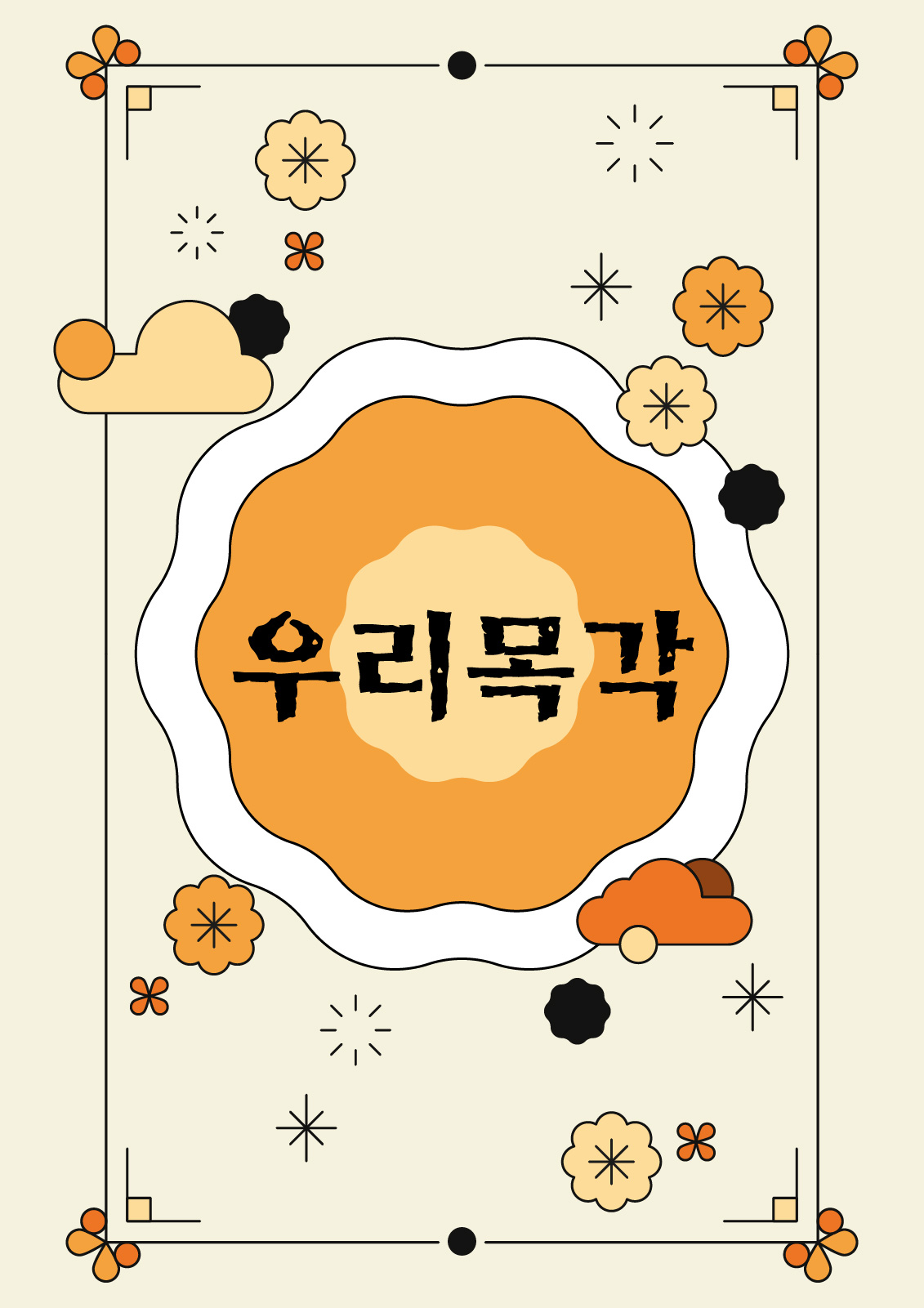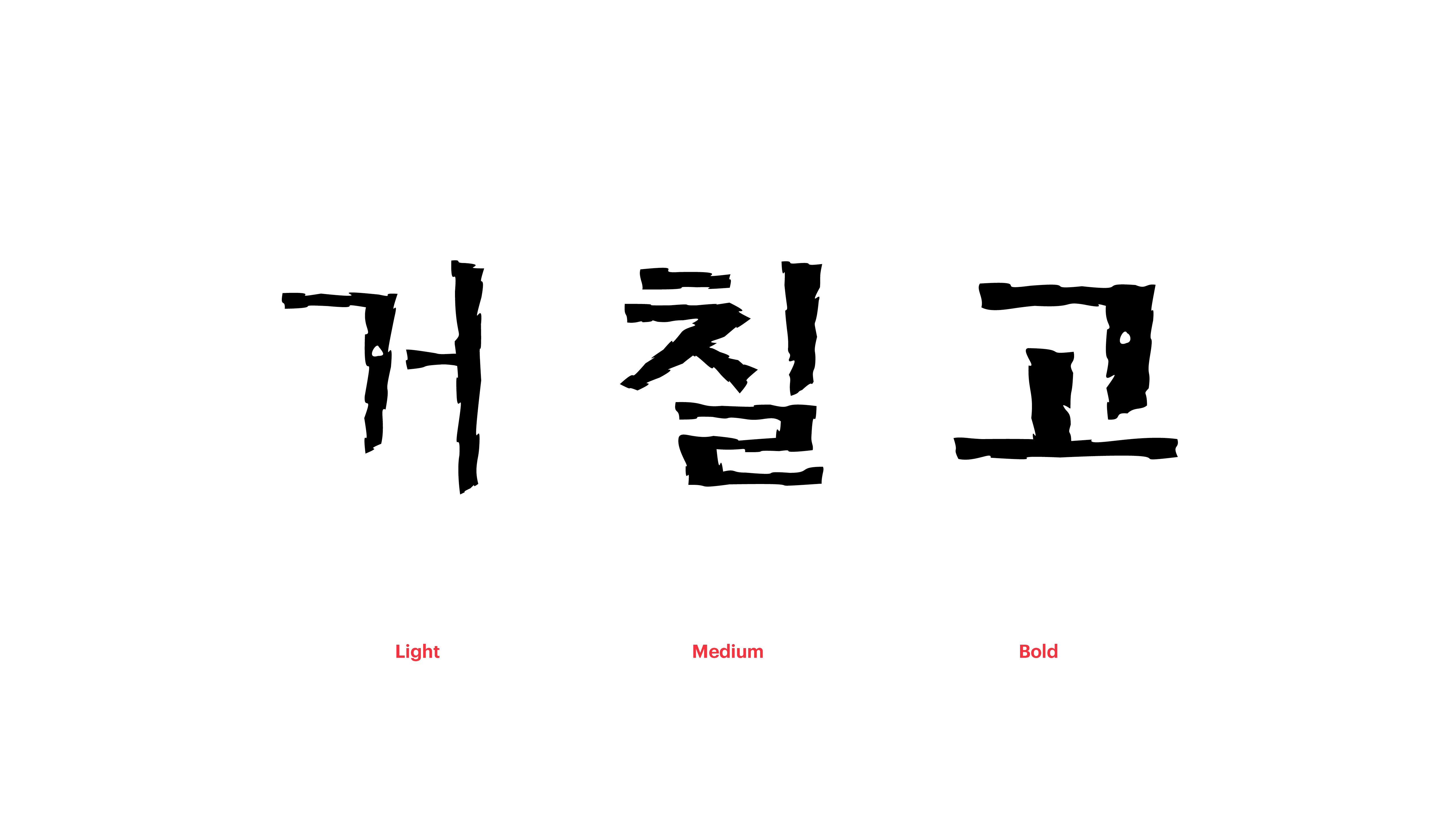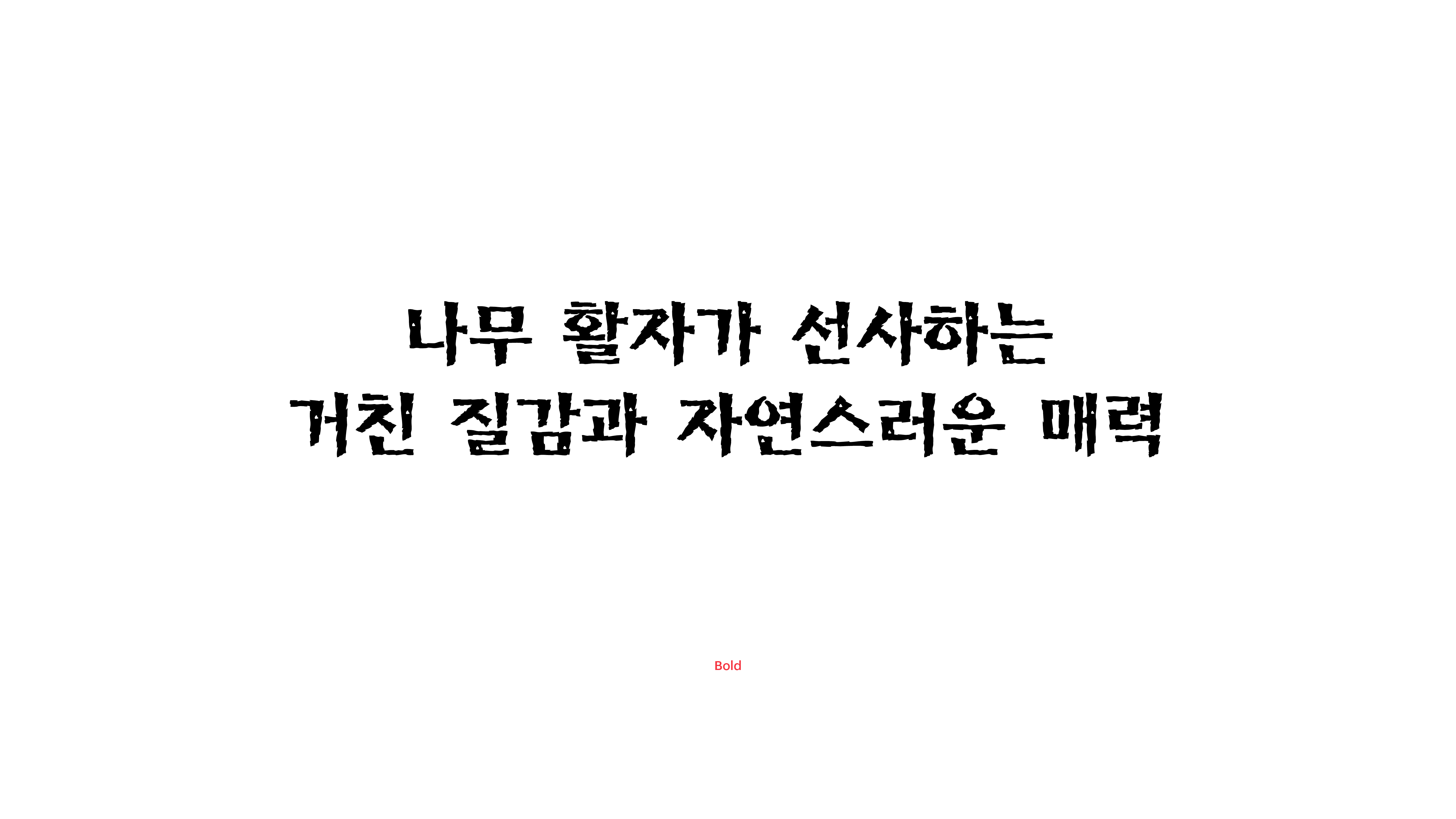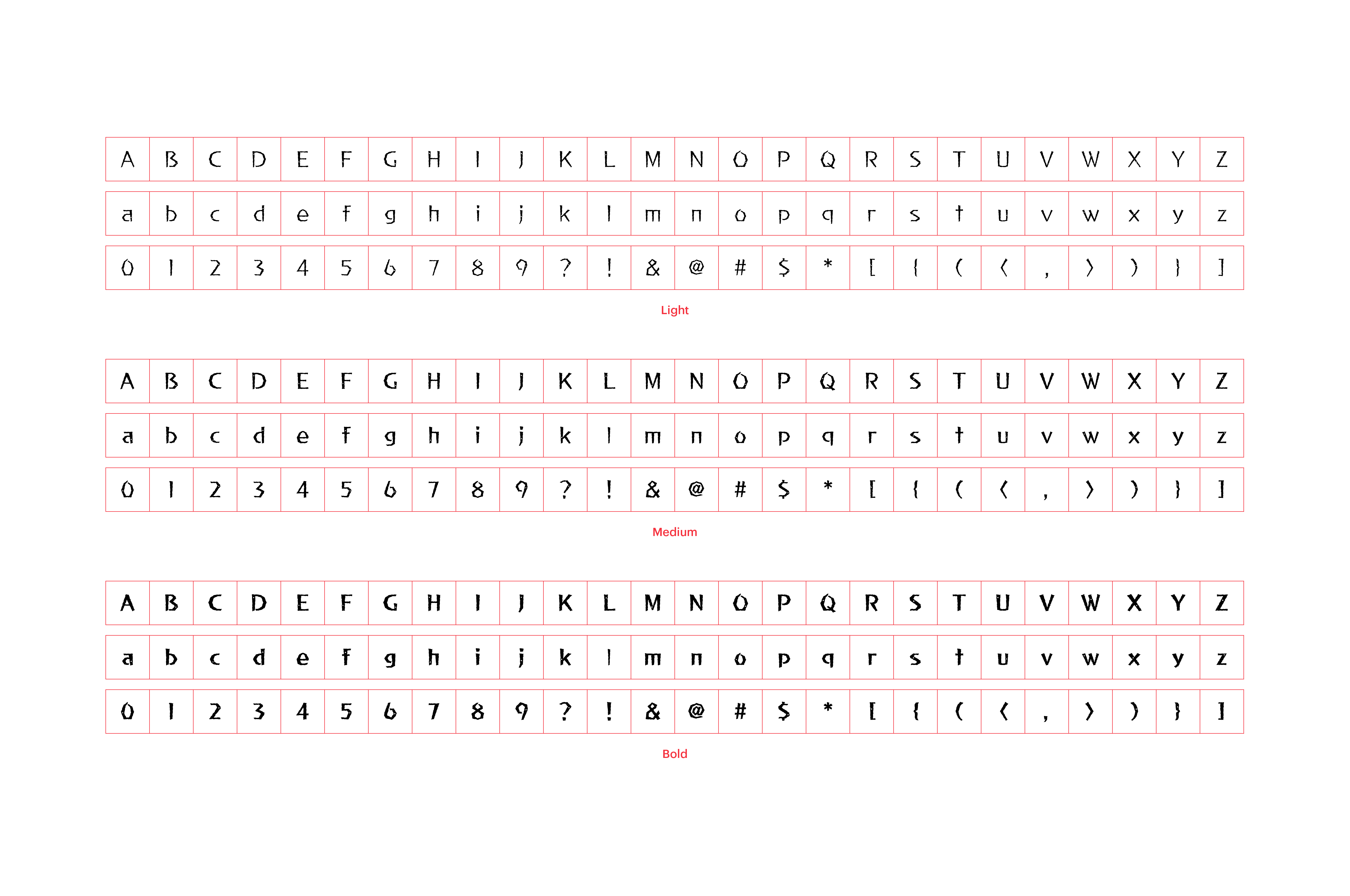
과거에는 한글 소설을 목판에 새겨 간행하는 일이 성행하였습니다.* 나무판에 글자를 새기기 쉽도록 단순화한 모양에서는 특유의 소박한 멋이 느껴지지요. 나무 활자가 선사하는 거친 질감과 자연스러운 매력. 옛이야기를 읽듯 편안하게 즐겨보세요. *방각본체 : 1800년대 말과 1900년대 초에 지방의 일반인들이 한글 소설을 목판에 새겨 간행한 것을 방각본이라고 불렀다. 이 책에 나타나는 한글 글꼴을 방각본체라고 한다.
Yoon 우리목각